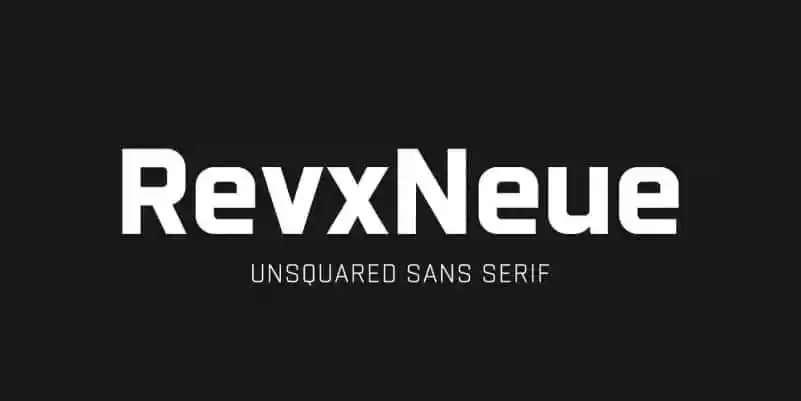
Revx Neue Sans Serif Font Demo – Download Grátis
A Revx Neue Sans Serif é uma tipografia sem serif moderna com oito estilos, incluindo sete tipos rectos que correspondem à suas itálicas. Este tipo foi projetado para oferecer um conjunto poderoso de características do OpenType Latin Pro, como alternativas de letras e parais da caligrafia, tornando-a uma fonte versátil e eficaz para diversas aplicações, incluindo web, apresentações visuais, impressão, entre outros. O designer onesevenpointfive criou um conjunto completo de estilos que se adapta perfeitamente a todos os ambientes digitais modernos. Seja para uma identidade visual sofisticada ou um design simples e dinâmico, a Revx Neue Sans Serif oferece uma solução precisa e elegante para qualquer necessidade de projeto.